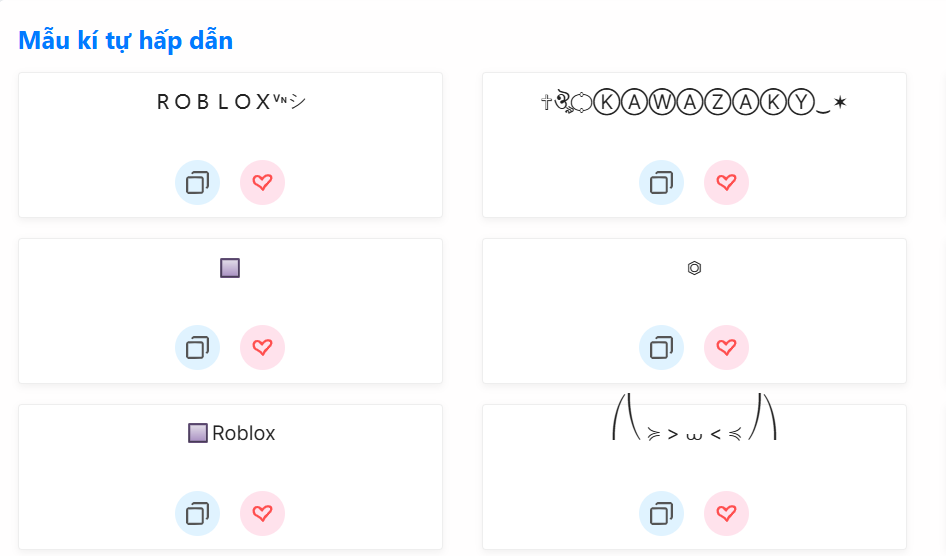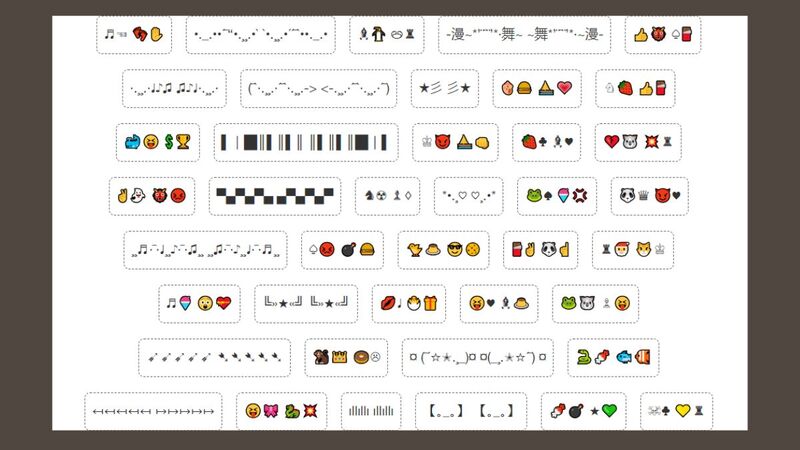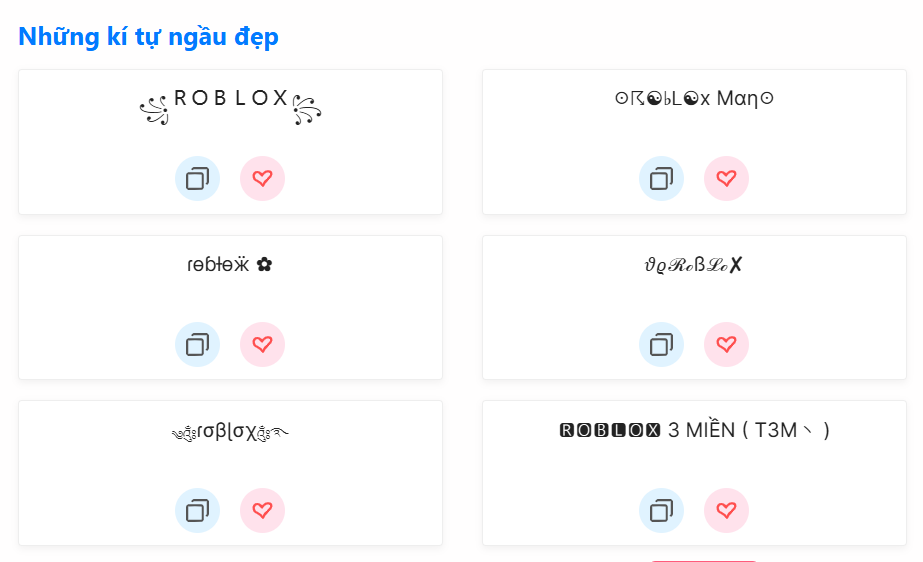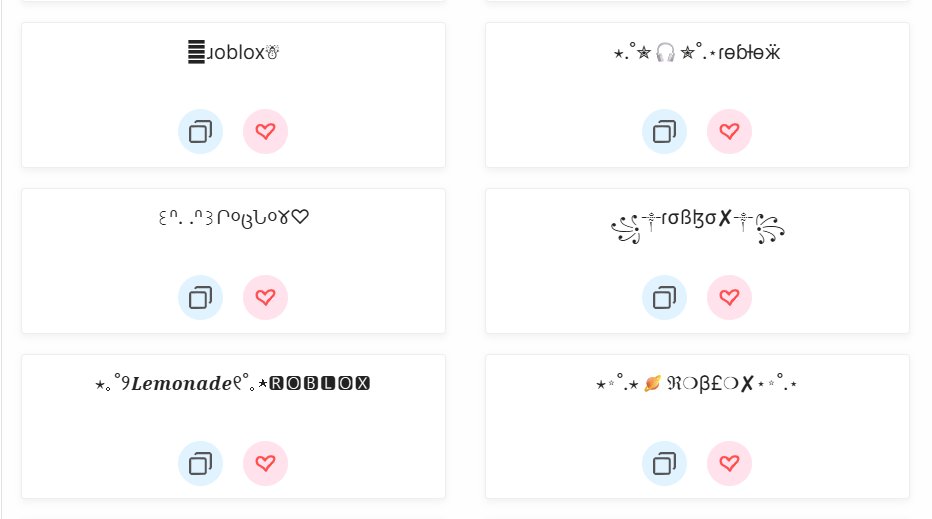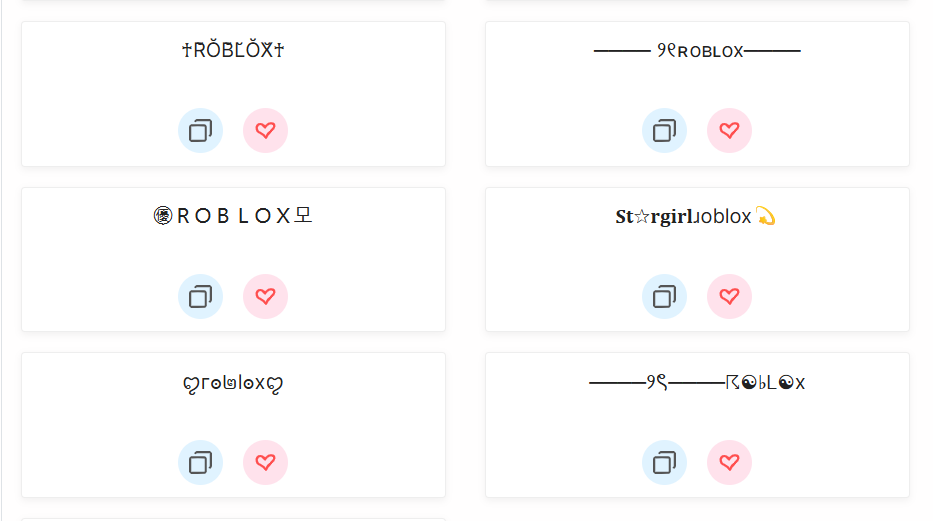
Tạo tên Roblox đẹp cùng bộ sưu tập kí tự đặc biệt tại Mobifonts.com. Tạo tên acc cực ngầu với kí tự đặc biệt Roblox ngay tại đây!
Kí tự đặc biệt Roblox là những biểu tượng, ký hiệu và chữ cái Unicode đặc biệt được sử dụng để tạo ra những tên độc đáo và ấn tượng trong game Roblox. Những kí tự đặc biệt trong Roblox này đóng vai trò quan trọng trong việc giúp người chơi thể hiện cá tính riêng và tạo sự khác biệt trong cộng đồng game đông đảo.
Bài viết sẽ chia sẻ bộ sưu tập các kí hiệu Roblox hot nhất 2025 bao gồm kí tự đẹp, kí hiệu đặc biệt Roblox hình sao, kí tự khoảng trống, mẫu kí tự cho Nam và Nữ từ cool ngầu đến dễ thương. Cùng với đó là hướng dẫn tạo tên kí tự đặc biệt Roblox nhanh chóng và giải đáp các thắc mắc về quy định sử dụng kí tự trong Roblox.
Năm 2025 chứng kiến sự bùng nổ của các tên kí tự đặc biệt Roblox với nhiều kiểu dáng và phong cách kí tự đẹp, hình ngôi sao, khoảng trống. Roblox hỗ trợ đa dạng các loại ký tự Unicode, tạo cơ hội vô hạn để người chơi thể hiện cá tính thông qua tên của mình.
Những kí hiệu đặc biệt Roblox đẹp mắt luôn được ưa chuộng bởi tính thẩm mỹ cao và khả năng tạo ấn tượng mạnh trong cộng đồng game thủ. Các ký tự này thuộc nhóm "Miscellaneous Symbols" và "Dingbats" trong hệ thống Unicode, được thiết kế để tạo ra hiệu ứng trang trí và làm đẹp cho văn bản.
Kí tự đặc biệt trong Roblox đẹp thường bao gồm các biểu tượng hoa văn, trái tim, ngôi sao và các hình học nghệ thuật, kết hợp hoàn hảo giữa vẻ đẹp visual và tính độc đáo.
Bộ ký tự hoa văn:
Ký tự trái tim lãng mạn:
Một số ý tưởng tên Roblox sử dụng kí hiệu Roblox đẹp mắt và lãng mạn như: ✧Angel✧Princess✧, ♡Sweet♡Girl♡, ❀Flower❀Queen❀, ✿Cherry✿Blossom✿,…
Kí hiệu Roblox hình sao tạo ra hiệu ứng lấp lánh và thu hút, đặc biệt phù hợp với những ai muốn thể hiện sự nổi bật và đẳng cấp trong game. Những biểu tượng ngôi sao này thuộc nhóm "Star and Asterisk" trong hệ thống Unicode, ban đầu được thiết kế để làm dấu hiệu chú thích và trang trí văn bản.
Lý do hạn chế:
Tương thích với đa nền tảng như PC, mobile, console,...
Tránh nhầm lẫn với ký tự hệ thống
Tuân thủ chính sách an toàn cộng đồng